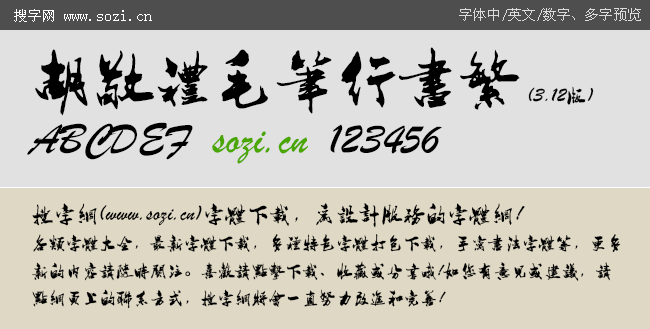
胡敬禮毛筆行書(shū)繁
搜字網(wǎng)提供一款胡敬禮毛筆行書(shū)繁中文書(shū)法字體下載,胡敬禮毛筆行書(shū)繁是一款手寫(xiě)風(fēng)格的書(shū)法字體,字體瀟灑大氣,整體效果非常出色,適合應(yīng)用于廣告設(shè)計(jì)、名片設(shè)計(jì)、包裝印刷、產(chǎn)品設(shè)計(jì)等應(yīng)用。